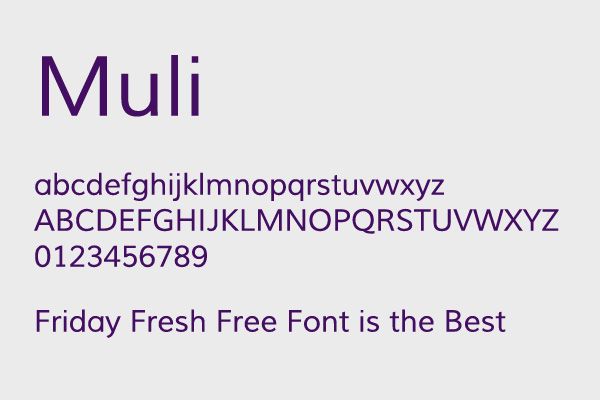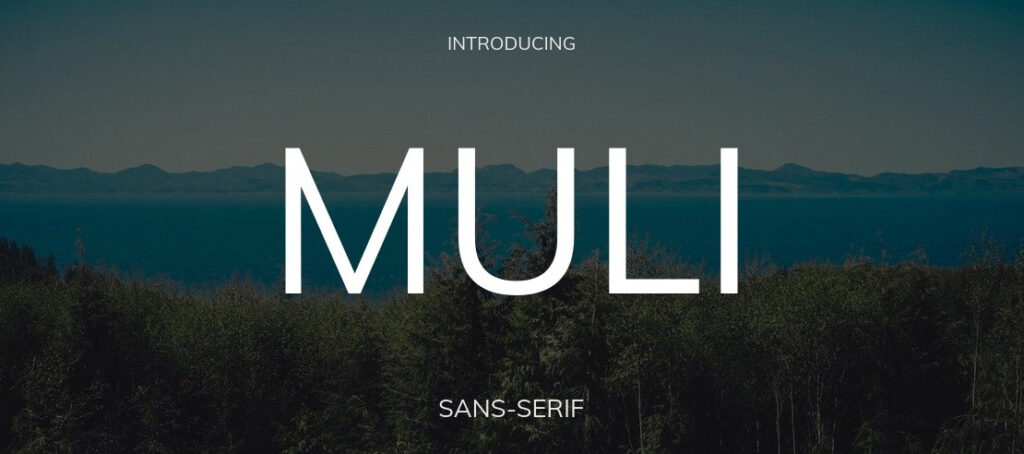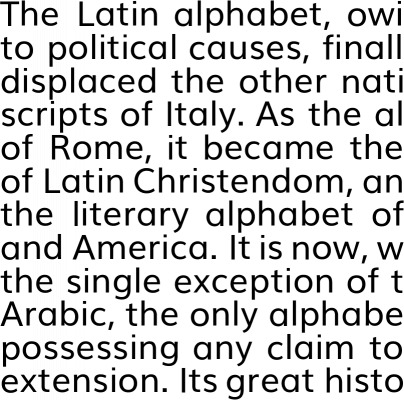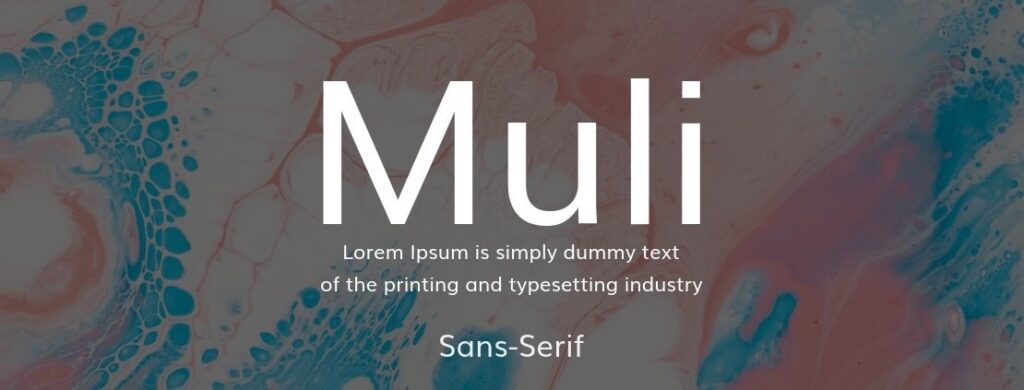
Font Muli việt hóa mang đến cho các kiến trúc sư và nhà thiết kế một giải pháp phông chữ không chân theo trường phái tối giản, nổi bật với tỷ lệ chữ mở rộng và các đường nét thanh thoát. Được sáng tạo bởi Vernon Adams, kiểu chữ này được tối ưu hóa cho khả năng hiển thị rõ ràng trên cả màn hình kỹ thuật số lẫn các bản in kỹ thuật.
Tỷ lệ mở thoáng đãng và khả năng nhận diện cao của font Muli Việt hóa
Điểm cuốn hút của font Muli Việt hóa nằm ở cấu trúc hình học mềm mại, các góc nối chữ được gọt giũa tỉ mỉ để tạo ra không gian thoáng đãng bên trong lòng ký tự (open counters). Nhờ chiều cao ký tự (x-height) cân đối, Muli duy trì được khả năng đọc êm ái khi trình bày các khối văn bản dài mà không gây mỏi mắt cho người xem.
Sự ổn định về mặt thị giác của dòng font này giúp truyền tải thông điệp về sự minh bạch, logic và tư duy làm việc bài bản. Khi xuất hiện trên các bề mặt vật liệu kiến trúc hiện đại như tấm panel tôn phẳng sơn tĩnh điện, vách kính hay biển chỉ dẫn alu trong các văn phòng container, Muli tạo nên diện mạo tinh gọn và chuẩn mực.
| Phân loại phong cách | Minimalist Sans-serif / Modern / Text & Display |
| Mục đích phù hợp | Ghi chú bản vẽ CAD, thuyết minh dự án, website |
Tư vấn từ chuyên viên: Muli sở hữu phong cách trung tính và cực kỳ dễ đọc. Để bản thiết kế đạt hiệu quả thẩm mỹ tốt, bạn nên dùng các biến thể Bold cho các đầu mục chính và sử dụng kiểu Regular cho nội dung thuyết minh chi tiết. Sự phân tầng rõ ràng này sẽ giúp hồ sơ dự án của bạn trông khoa học và dễ tra cứu thông tin hơn.
03 Ứng dụng phông chữ Muli vào thực tế kiến trúc
Nhờ vẻ ngoài sáng sủa và tính đa năng cao, bộ phông chữ này mang lại giá trị thực tế lớn trong khâu quản lý và triển khai các dự án hiện đại:
- Ghi chú thông số trên bản vẽ AutoCAD: Độ sắc sảo của Muli giúp các dòng chú thích kích thước vật liệu panel, thông số kết cấu thép trở nên rõ nét, hỗ trợ đội ngũ giám sát thi công tại hiện trường tra cứu thông tin nhanh chóng.
- Hệ thống biển chỉ dẫn cho Văn phòng Container: Những nét chữ không chân hiện đại của Muli rất ăn ý khi gia công trên biển mica hoặc decal dán kính, giúp không gian làm việc toát lên vẻ ngăn nắp và chuyên nghiệp.
- Hồ sơ năng lực và Báo cáo dự toán công trình: Sử dụng font Muli cho các bảng biểu tính toán giúp các con số hiển thị tách bạch, tạo ấn tượng về một đơn vị có quy trình vận hành minh bạch và tư duy thẩm mỹ cao.
Để khai thác hiệu quả vẻ đẹp của dòng font Sans-serif tối giản này mà không gây cảm giác đơn điệu cho trang in, người thiết kế nên lưu tâm một số kinh nghiệm sau:
- Kiểm soát khoảng cách dòng: Với cấu trúc ký tự mở rộng của Muli, bạn nên thiết lập khoảng cách dòng thoáng đãng (khoảng 1.4 – 1.5 lần cỡ chữ) để các dòng văn bản không bị dính nét, giúp người đọc tiếp nhận thông tin dễ dàng.
- Phân cấp thông tin bằng độ đậm nét: Hãy tận dụng các biến thể từ Light, Regular đến Bold để làm nổi bật các hạng mục quan trọng mà không cần phải thay đổi quá nhiều kiểu chữ khác nhau trong cùng một trang tài liệu.
- Đồng bộ phông chữ trên mọi nền tảng: Duy trì sử dụng Muli từ hồ sơ bản vẽ kỹ thuật đến slide thuyết trình để tạo nên sự nhất quán và chuyên nghiệp trong nhận diện thương hiệu của đơn vị thi công.
FAQs – Thắc mắc thường gặp khi sử dụng phông chữ Muli
2. Sự khác biệt giữa phông chữ Muli và Mulish là gì?
Mulish chính là phiên bản nâng cấp chính thức của Muli trên Google Fonts, được bổ sung thêm nhiều cấp độ đậm nhạt và tối ưu hóa tốt hơn cho các màn hình kỹ thuật số độ phân giải cao.